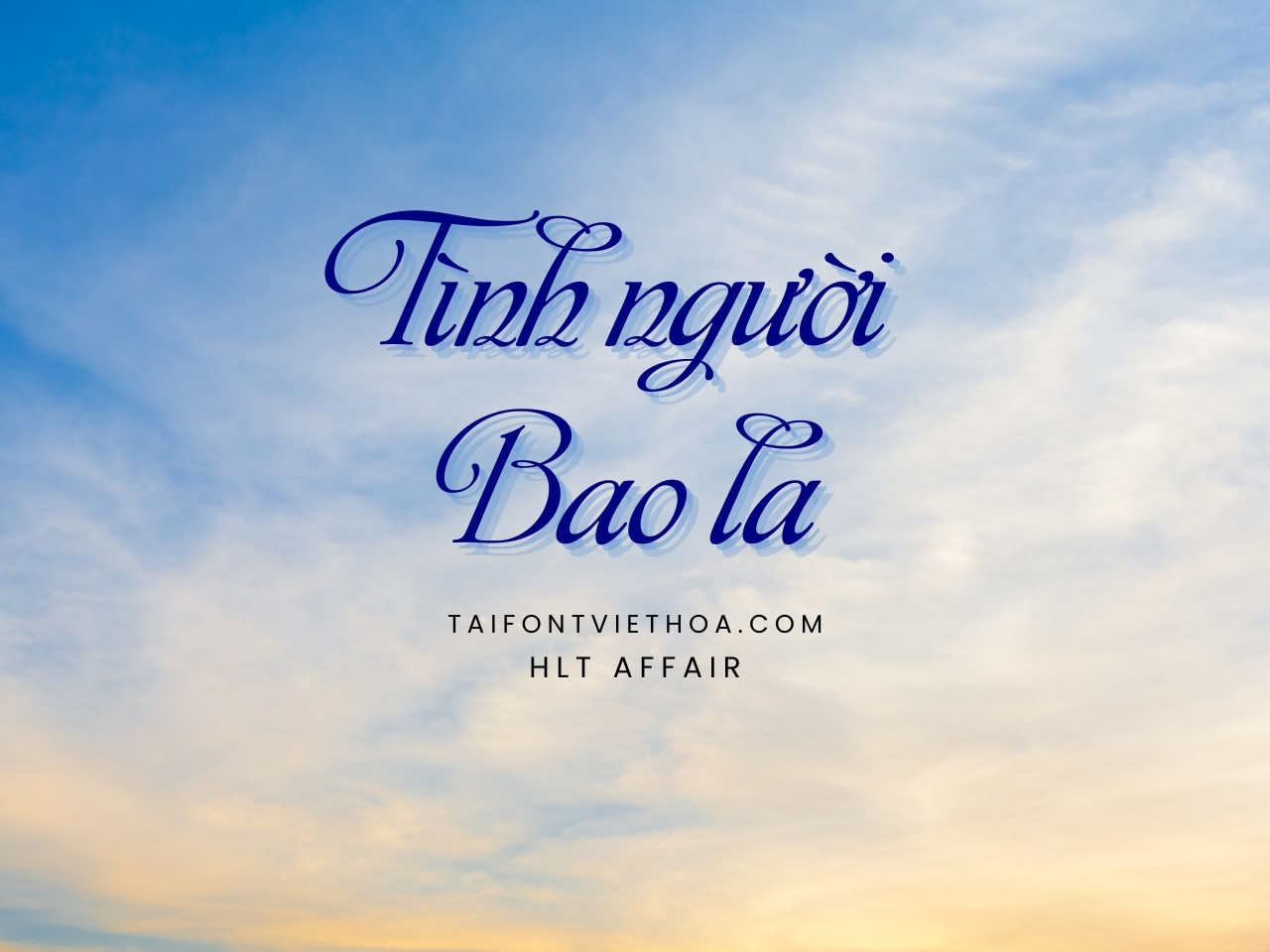
Font việt hóa HLT Affair
Giới thiệu về font HLT Affair – Kiểu chữ thư pháp bay bổng đầy nghệ thuật
HLT Affair là một kiểu font thư pháp hiện đại mang phong cách viết tay uốn lượn đầy mê hoặc, được thiết kế với cảm hứng từ những đường nét uyển chuyển của thư họa châu Âu. Font được Việt hóa bởi nhóm HLT, hỗ trợ đầy đủ tiếng Việt cùng với hơn 100 ngôn ngữ khác, cho phép áp dụng linh hoạt trong nhiều thiết kế toàn cầu. Với việc tích hợp bộ ký tự Latin mở rộng, font này không chỉ đáp ứng nhu cầu của cộng đồng thiết kế tại Việt Nam mà còn phục vụ cho các dự án quốc tế cần yếu tố cá nhân hóa và cảm xúc trong typography.
Đặc điểm thiết kế độc đáo và ứng dụng của font HLT Affair
HLT Affair gây ấn tượng với những đường nét mềm mại, thanh thoát, mang tính nghệ thuật cao. Các ký tự có độ nghiêng nhẹ, độ tương phản giữa nét đậm – nét mảnh rõ rệt, tạo nên cảm giác bay bổng và giàu cảm xúc. Font còn hỗ trợ ligatures và stylistic alternates, giúp nhà thiết kế có nhiều lựa chọn sáng tạo hơn trong dàn trang và tạo điểm nhấn thị giác.
Với cấu trúc chữ mô phỏng nét mực thật, HLT Affair đặc biệt phù hợp cho các dự án cần sự sang trọng, tinh tế hoặc mang tính chất cá nhân hóa cao. Một số ứng dụng điển hình gồm: thiết kế thiệp cưới, thư mời, typography nghệ thuật, bìa sách, logo thời trang cao cấp, bao bì sản phẩm handmade hoặc quảng bá thương hiệu trong lĩnh vực sáng tạo.